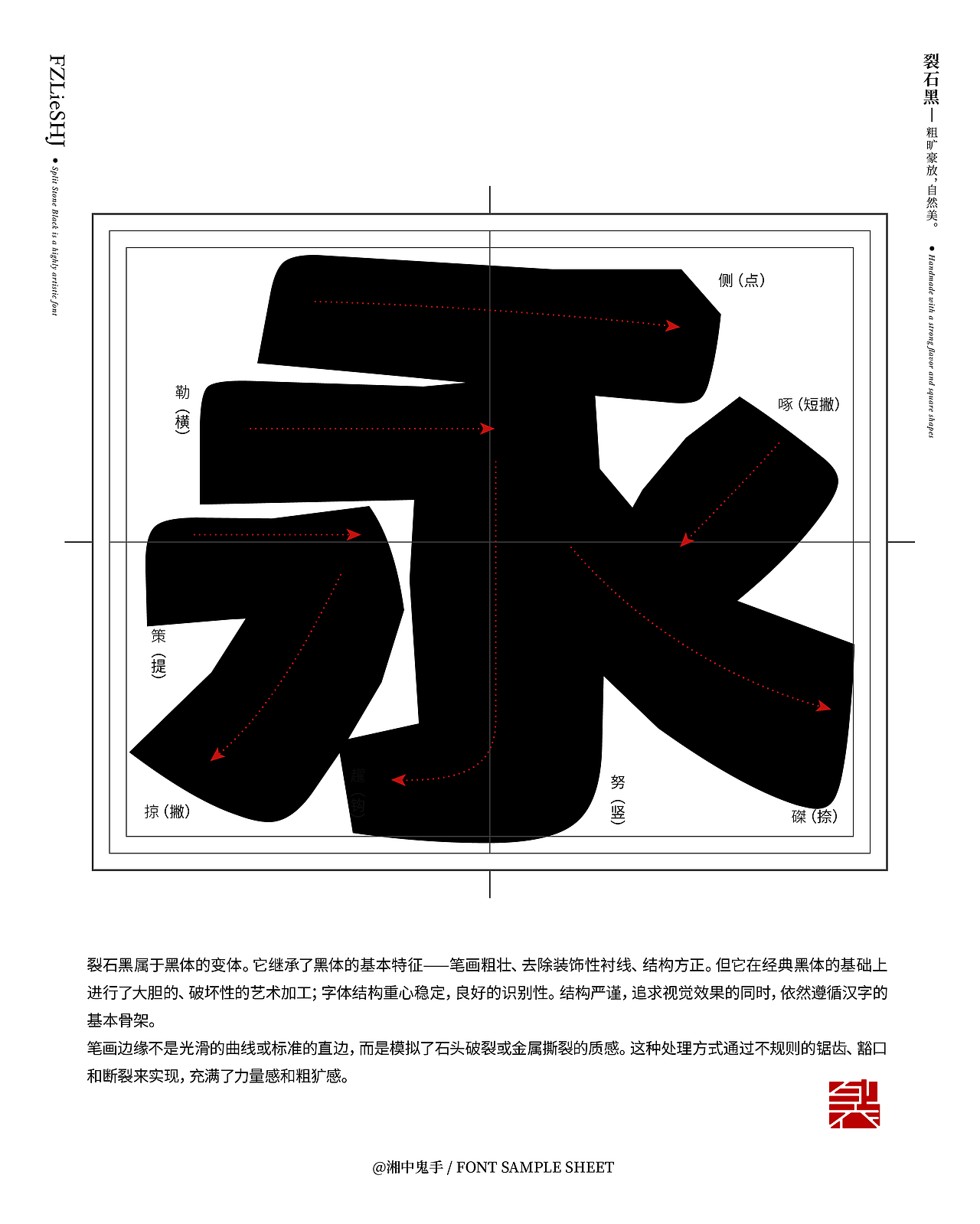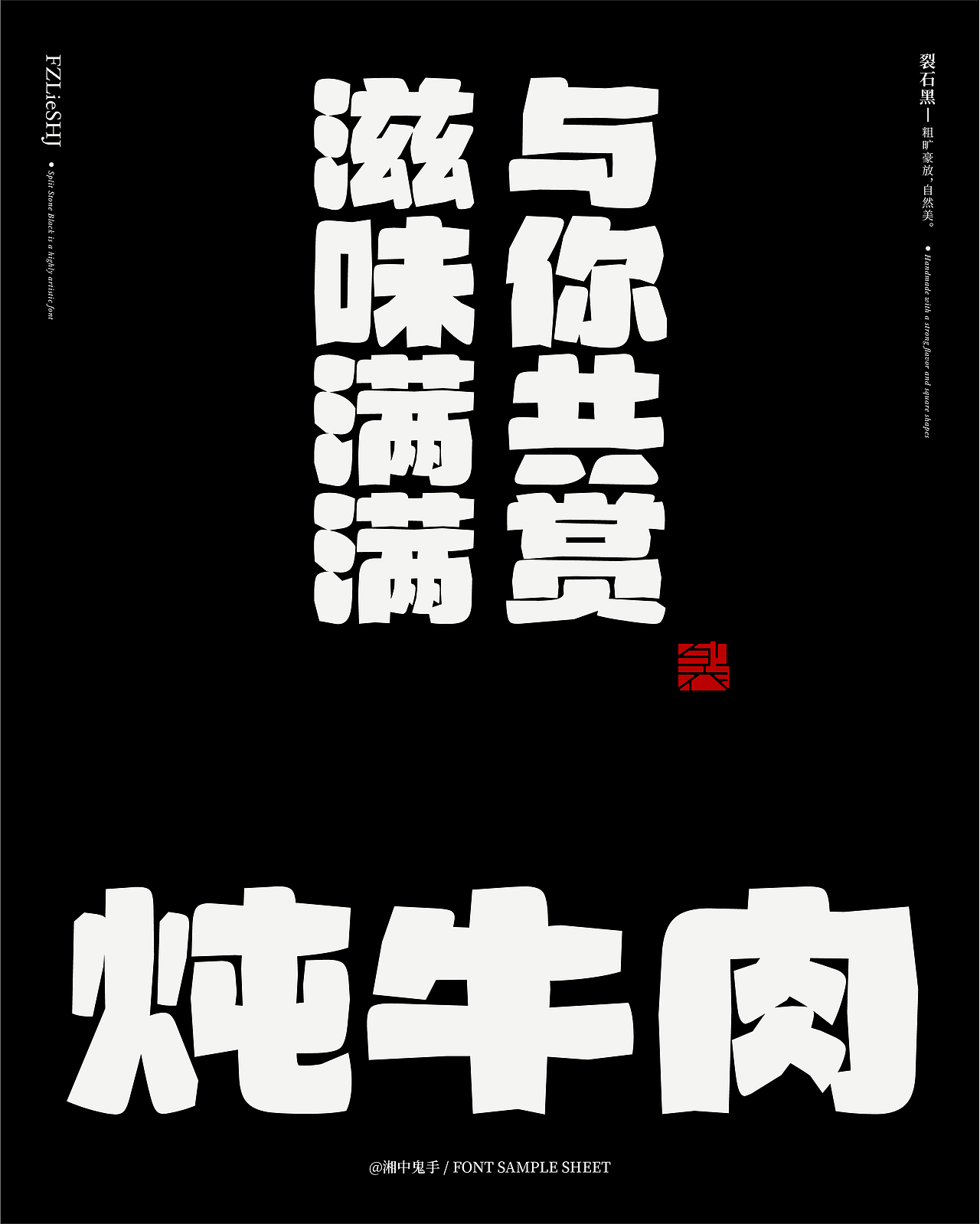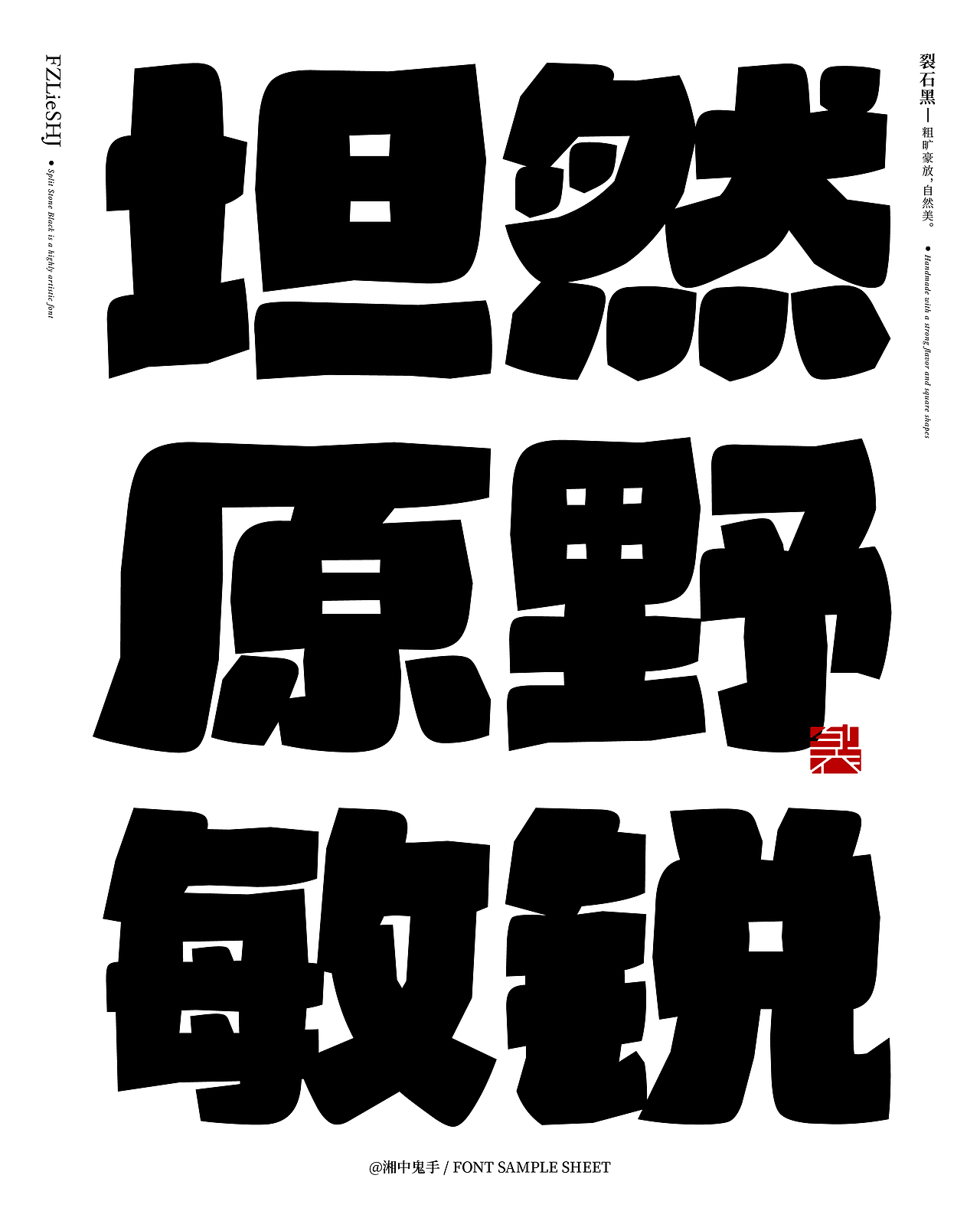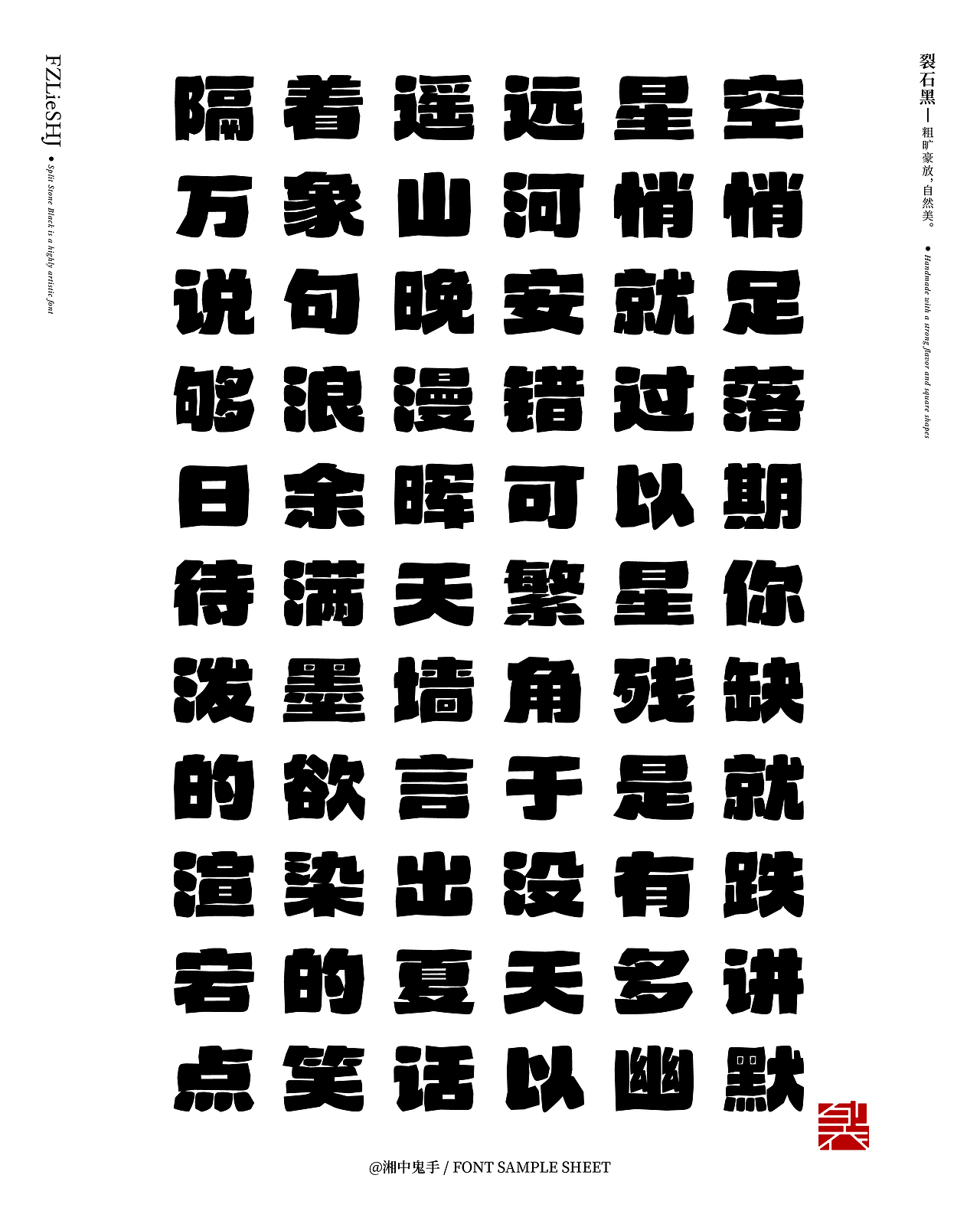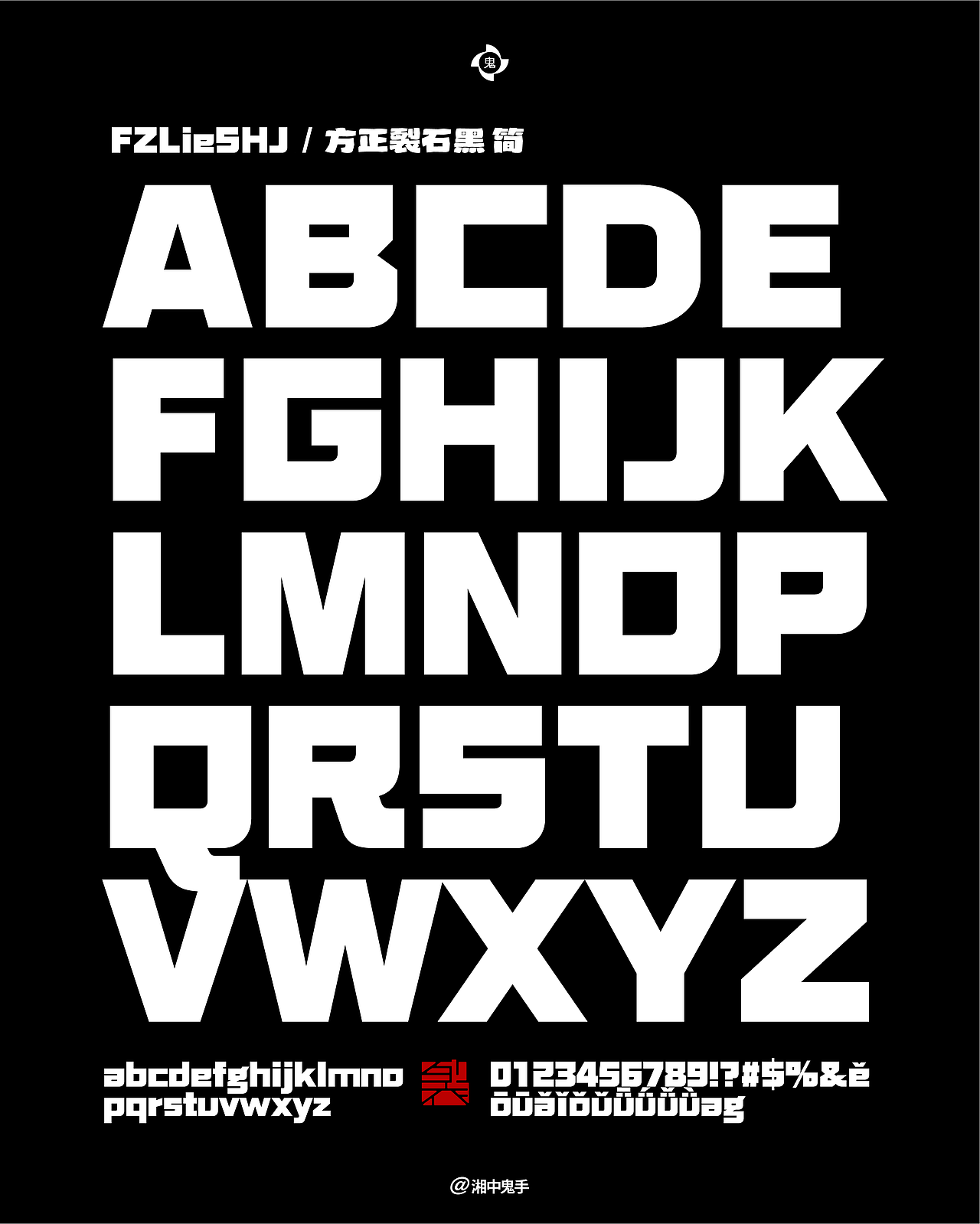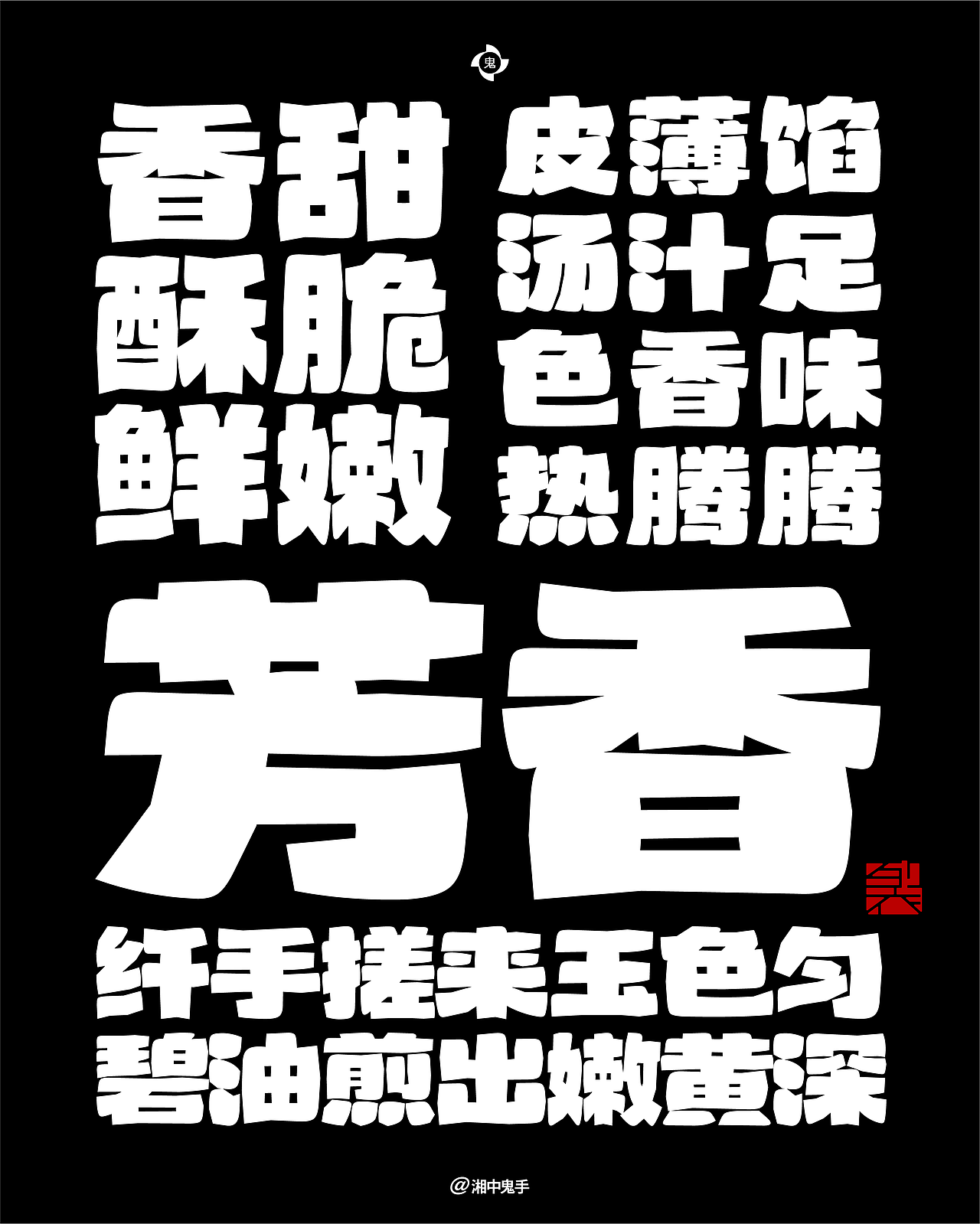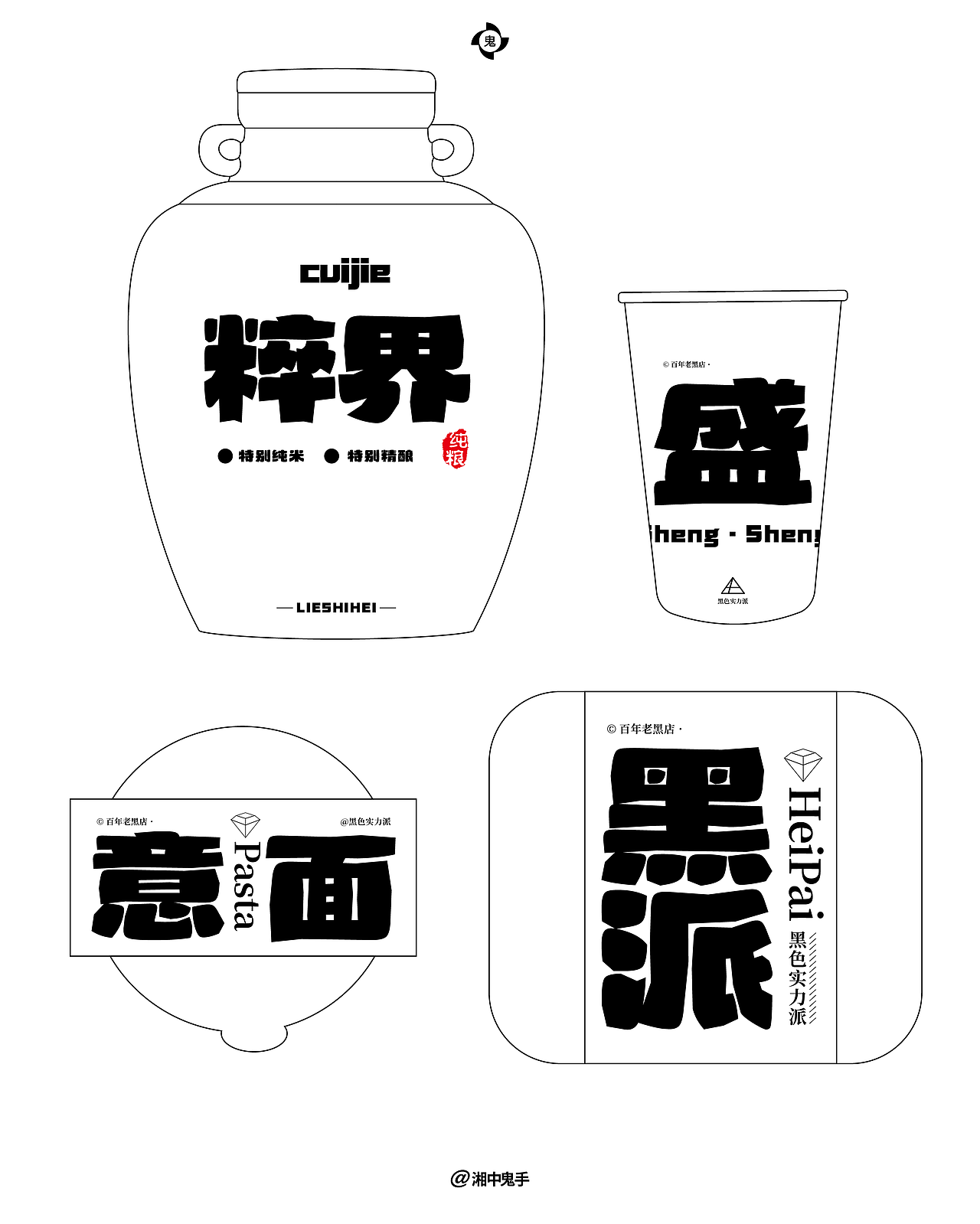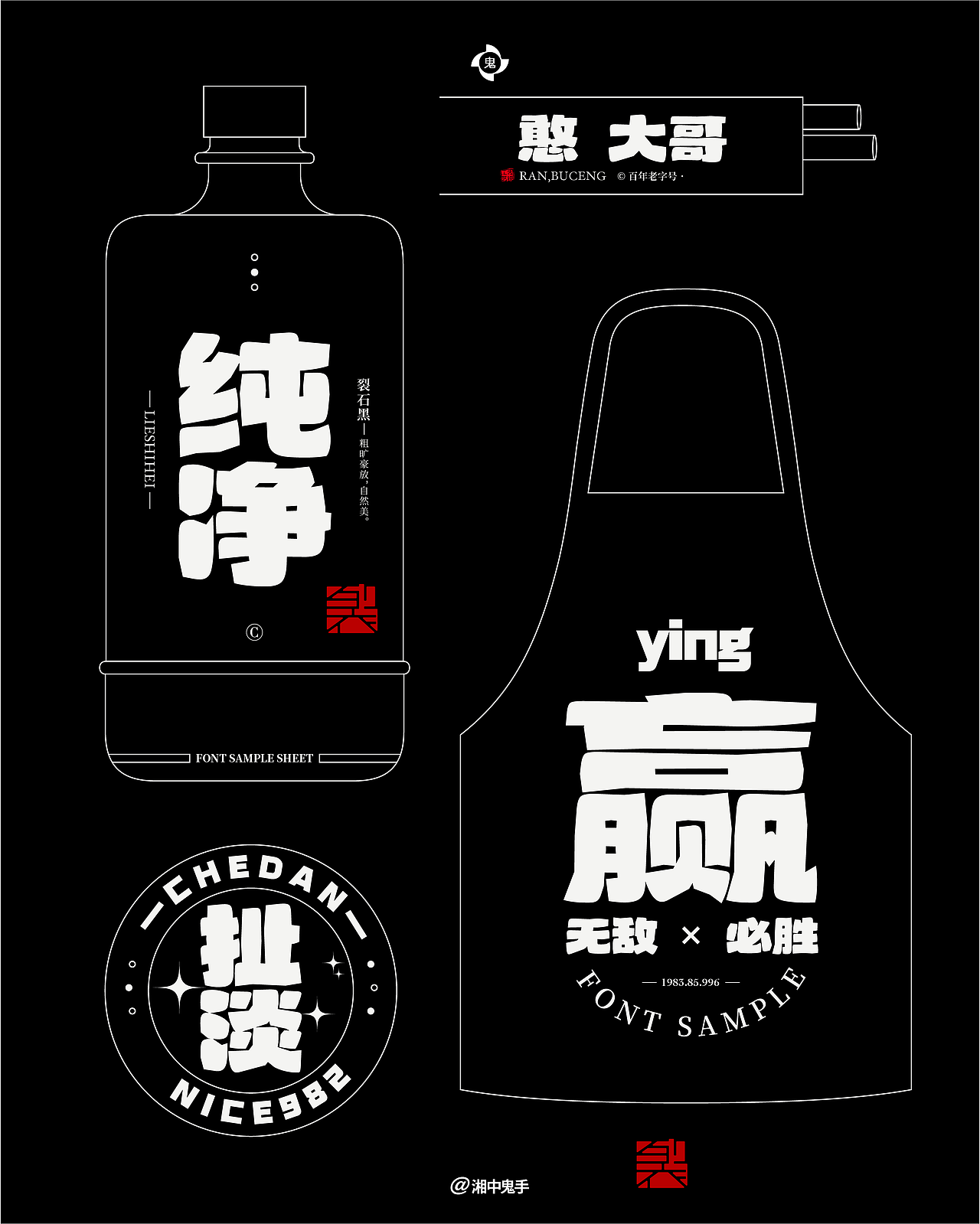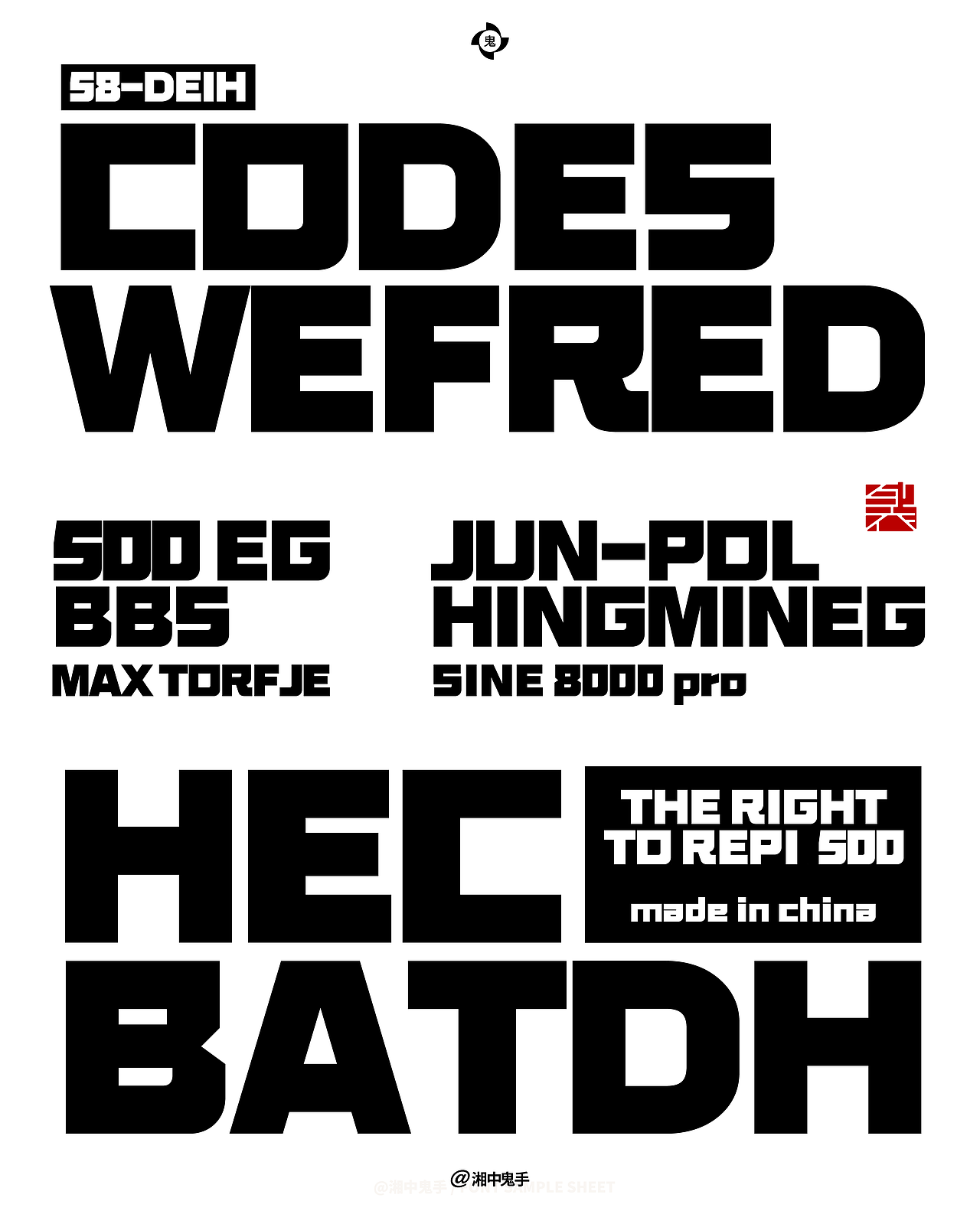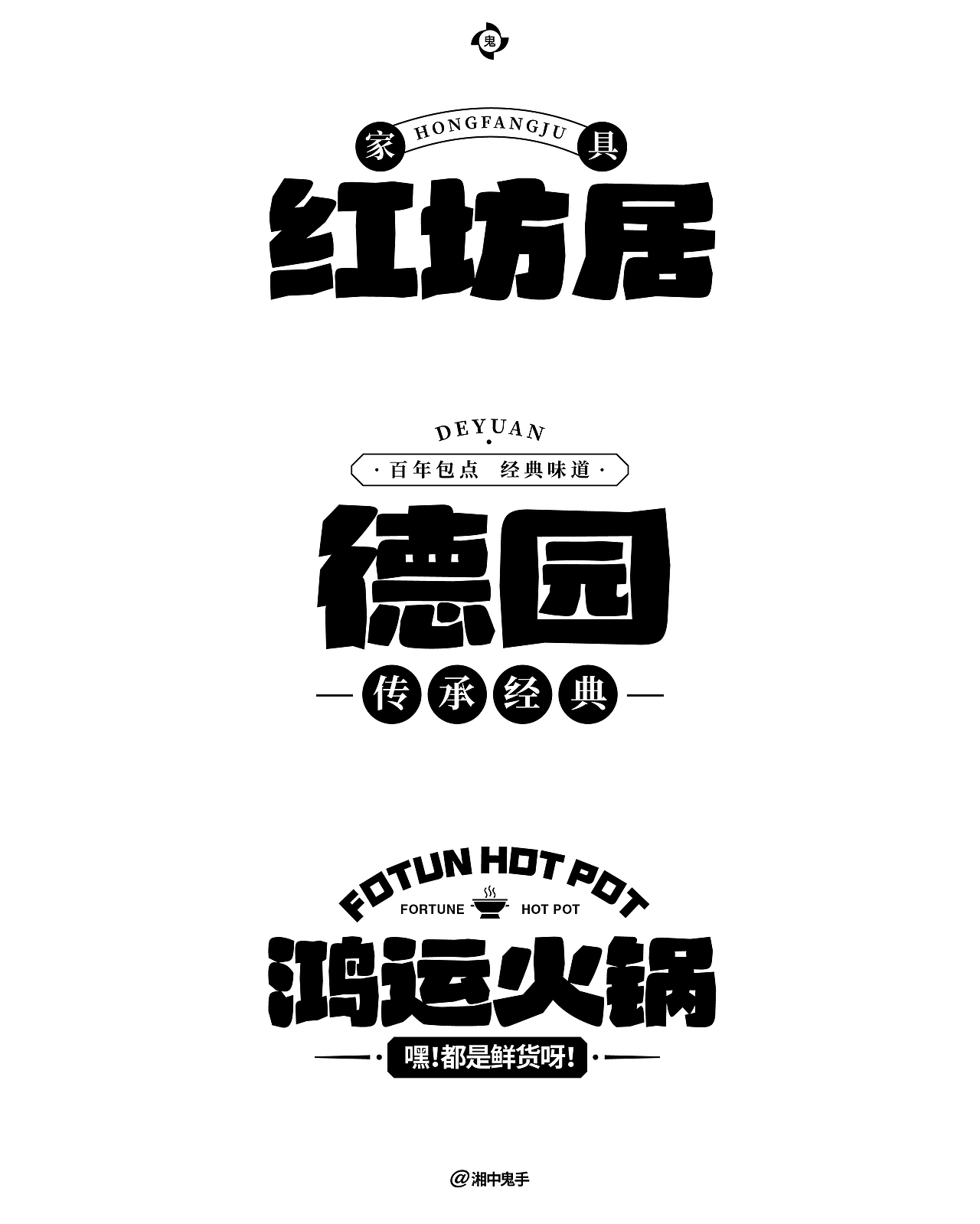
字库产品「方正裂石黑 简」
裂石黑是一款艺术性较强的字体,手工味道极浓,其字形方正,笔画似碎裂开的石头,故取名裂石黑;笔画表现出一种岁月的磨损感,隐含着历史古韵,笔画边缘不规则走向,若似自然形成的美;
由于笔画极其厚重,字体内部的留白(即负空间)被压缩到极致,形成了强烈的黑白对比。这些被挤压出的负空间形状也因笔画的“裂痕”而变得不规则,增加了视觉的复杂性和趣味性。笔画粗旷豪放,整体统一性强,细节却颇有不同,经久耐看,灰度高,适用于各类广告标题字的应用。
感谢方正字库的专业支持,让这份对汉字力量的表达,正式与全国设计师见面。英文字符部分由方正字库团队完成